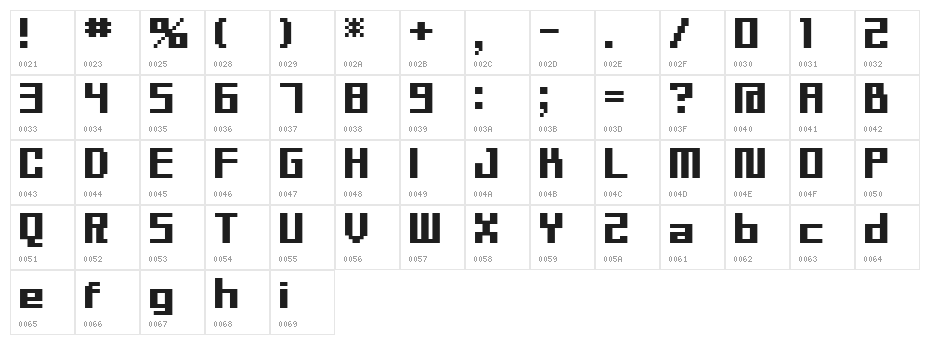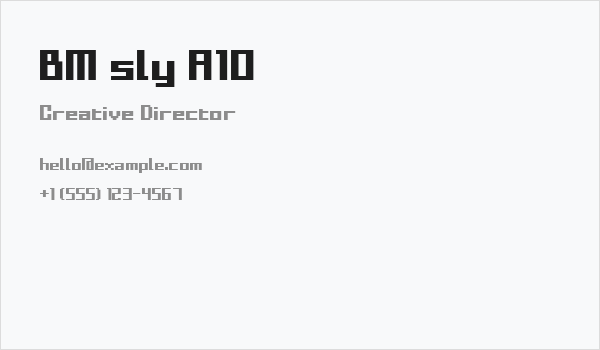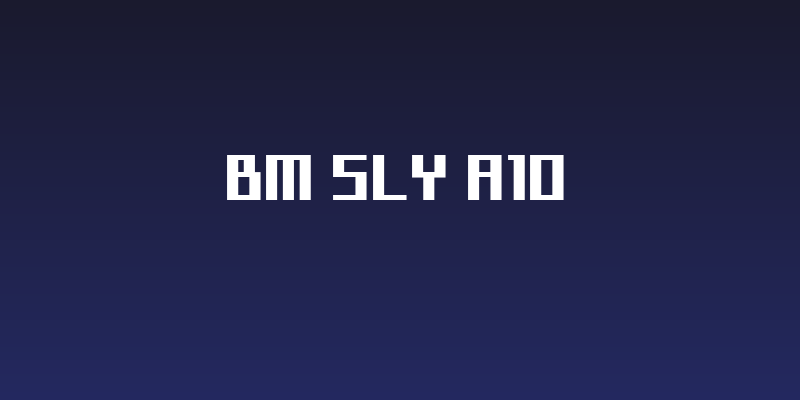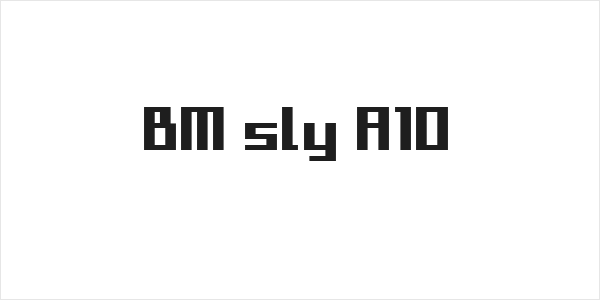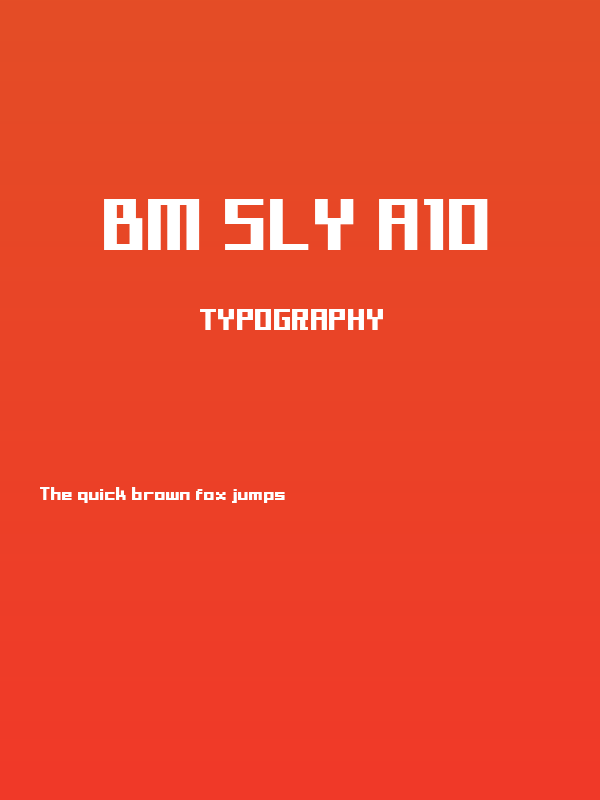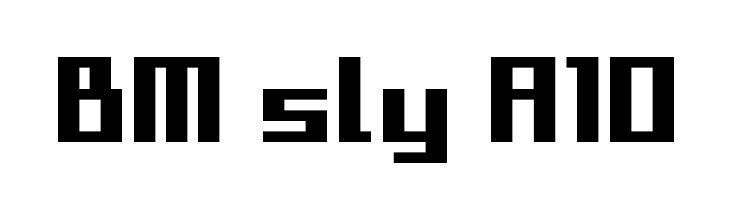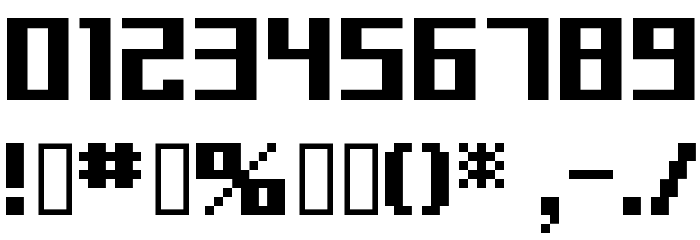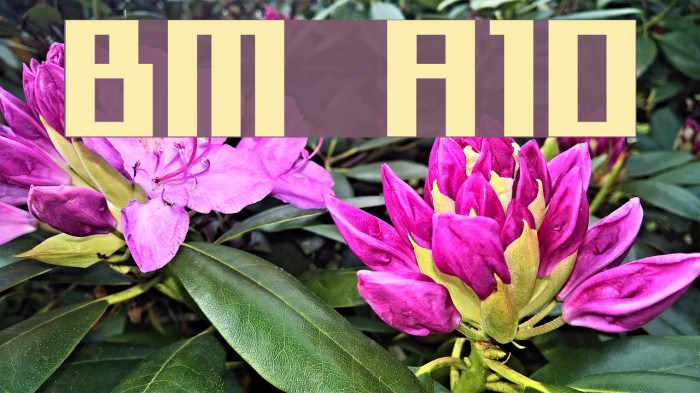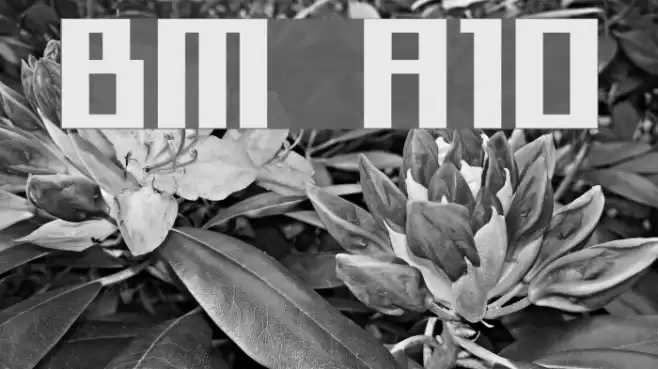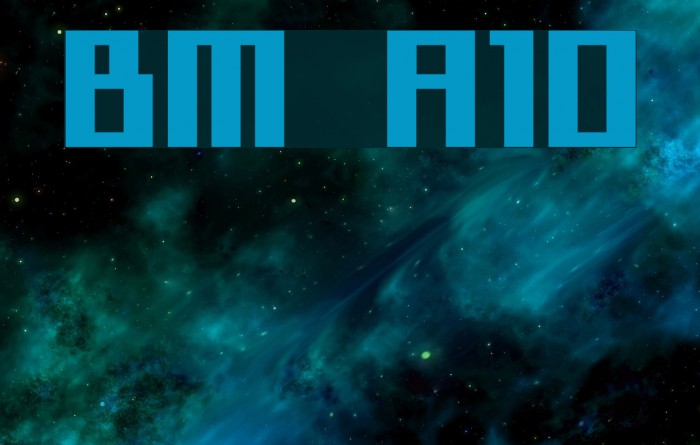
BM sly A10 Font
✎ Pixel
| 名前 | BM sly A10 |
| ウェイト | A10 |
| カテゴリ | Pixel |
| 全体的なスタイル | Retro, Digital |
| 用途 | Headlines, Logos, Digital displays |
| おすすめプロジェクト | Ideal for retro-themed designs, video game graphics, digital art projects, and tech-inspired branding. |